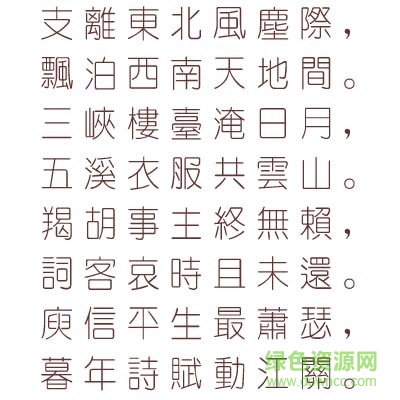
金橋繁細(xì)圓是金橋字體庫(kù)中的一款繁體字體。該字體筆畫細(xì),字形圓,整個(gè)風(fēng)格清晰,使用的人數(shù)也是很廣泛的,對(duì)于喜歡書法和設(shè)計(jì)的朋友來(lái)說(shuō)這是不錯(cuò)的字體,而且還十分的得體,喜歡的朋友,趕快下載體驗(yàn)吧!